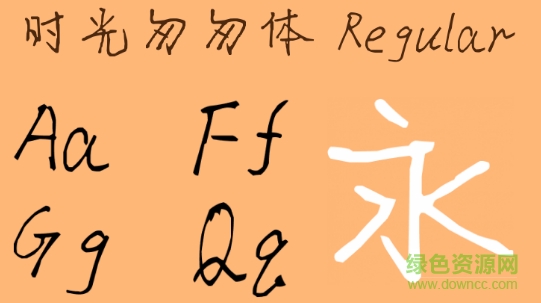
OPPO字體時(shí)光匆匆體ttf版是一款漂亮的手寫(xiě)字體,字體骨骼清秀,筆畫(huà)錯(cuò)落有致,簡(jiǎn)潔優(yōu)雅,廣告設(shè)計(jì)或網(wǎng)頁(yè)設(shè)計(jì)都用得到,喜歡這款字體的朋友快來(lái)綠色資源網(wǎng)下載吧!
大大小小,風(fēng)格不一,帶著體溫的書(shū)寫(xiě)出來(lái)的字體。
手寫(xiě)體文字是用“美工筆”在紙上寫(xiě)出來(lái)的,可能一個(gè)字會(huì)寫(xiě)幾十遍或者更多,之后再?gòu)闹虚g選出寫(xiě)的比較可以接受的拍照,上傳到電腦上用photoshop處理后制作而成。